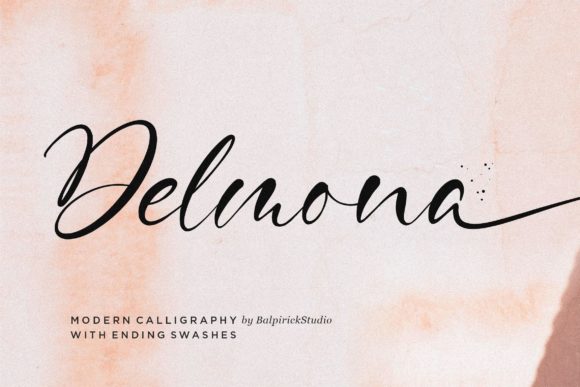
Creativefabrica Delmona Font
[Creativefabrica] Delmona Font
Delmona - это плавный рукописный шрифт, описанный элегантным прикосновением, идеально подходящий для ваших любимых проектов.
Влюбитесь в его невероятно четкий и неподвластный времени стиль и используйте его для создания эффектных дизайнов!